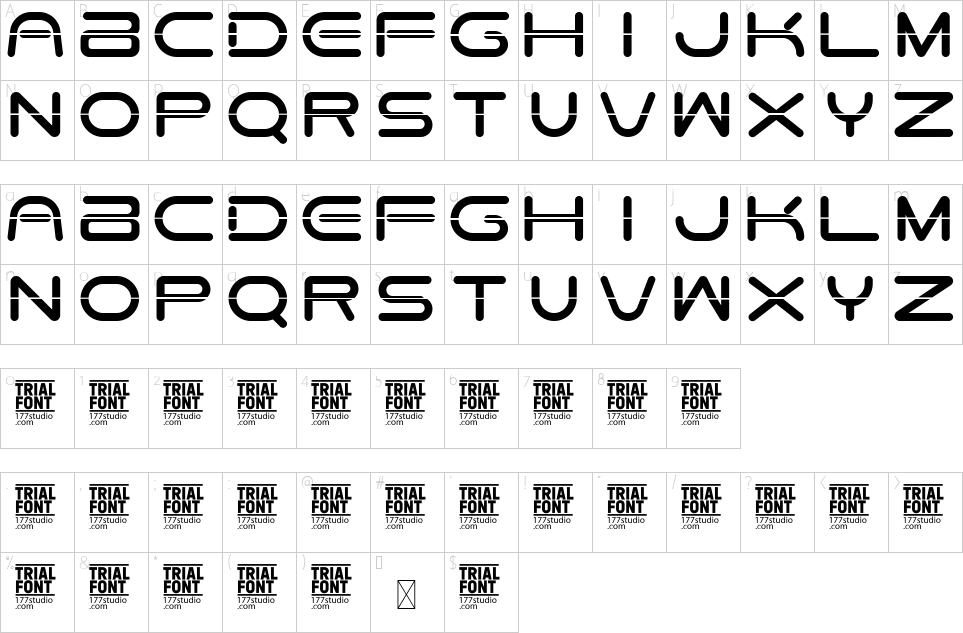
A fonte ‘Dates Detail’ oferece uma solução clara e elegante para personalizar suas informações data-relevantes. Desenvolvida por 177studio.com, esta fonte vem disponível tanto para sistemas Windows quanto Mac, facilitando seu uso diário. O design limpo da fonte garante legibilidade e uniformidade em qualquer documento ou projeto que você esteja trabalhando. Com um design cuidadosamente projetado, a ‘Dates Detail’ pode tornar sua apresentação de dados mais profissional sem comprometer a clareza necessária na leitura das datas. Inspirada nas necessidades dos usuários que procuram uma fonte prática para data-relevante tais como calendários ou notas pessoais, esta fonte foi projetada com precisão e facilidade de uso em mente. Com sua interface intuitiva e design moderno, ‘Dates Detail’ é um excelente complemento para qualquer projeto gráfico ou digital que precise de uma solução de fontes clara e confiável. Em suma, a ‘Dates Detail Font’ é uma fonte gratuita que proporciona grande flexibilidade ao usuário com um design sóbrio e funcional.